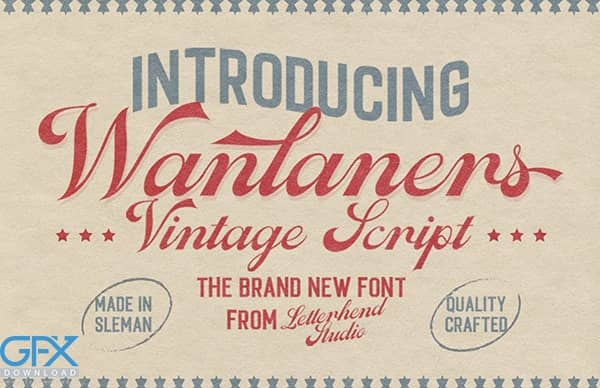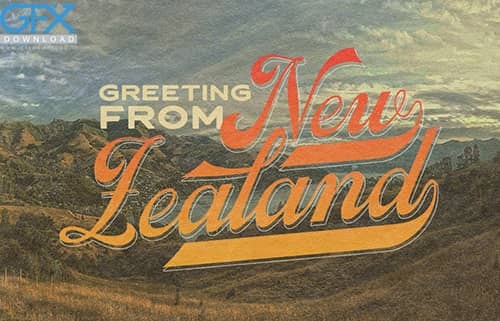
این نوع فونت به دلیل سبک خود احساس نوستالژیک و قدیمی دارد ، بنابراین این فونت قدیمی متناسب با پروژه های شما با موضوع قدیمی است. می توانید از آن برای ایجاد حروف زیبای قدیمی در یک ثانیه استفاده کنید. دانلود فونت قدیمی Wanlaners ساخته شده است تا برای طراحی در آرم و سایر موارد مختلف مانند دعوت نامه ، برچسب ، آرم ، مجله ، کتاب ، کارت تبریک / عروسی ، بسته بندی ، مد ، آرایش ، لوازم التحریر ، رمان ، برچسب یا هر نوع هدف تبلیغات به شما کمک کند. دارای حروف های بزرگ و کوچک ، اعداد و علائم نگارشی.
• شامل کاراکتر های بزرگ و کوچک • اعداد و علائم نگارشی • چند زبانه • لیگاتور • PUA رمزگذاری شده است